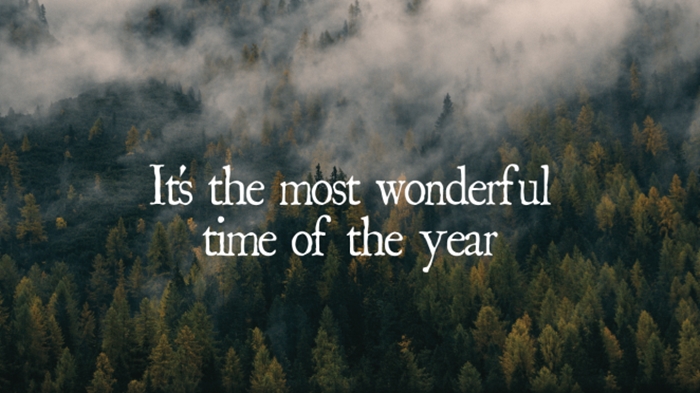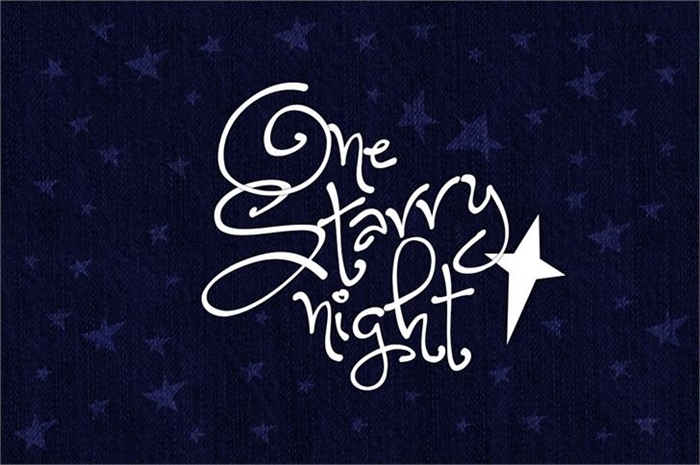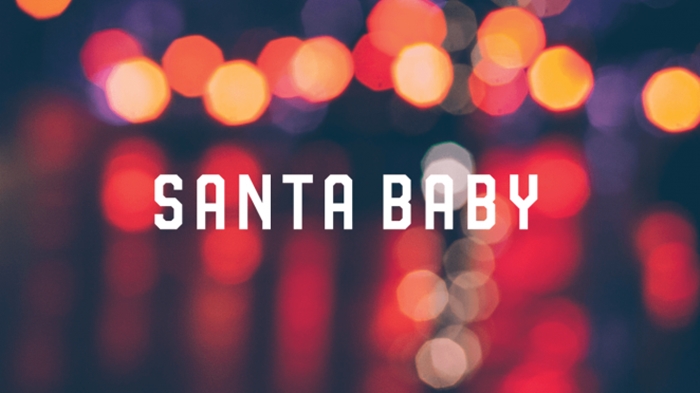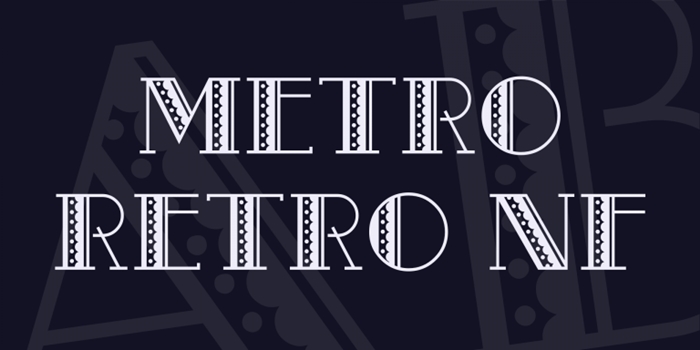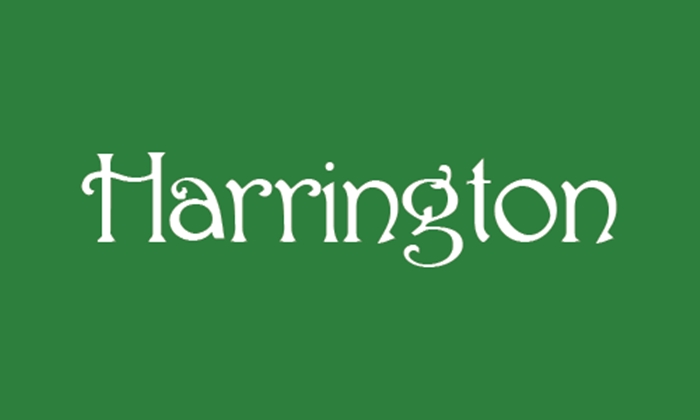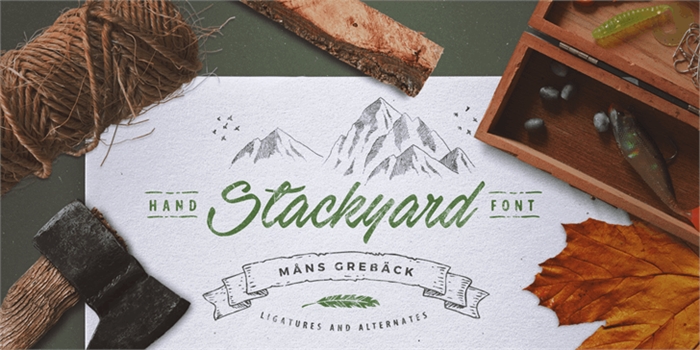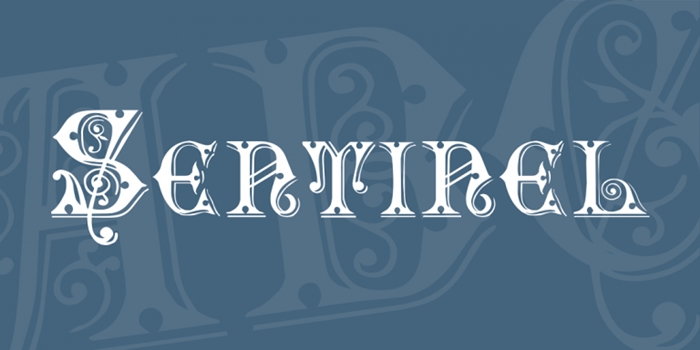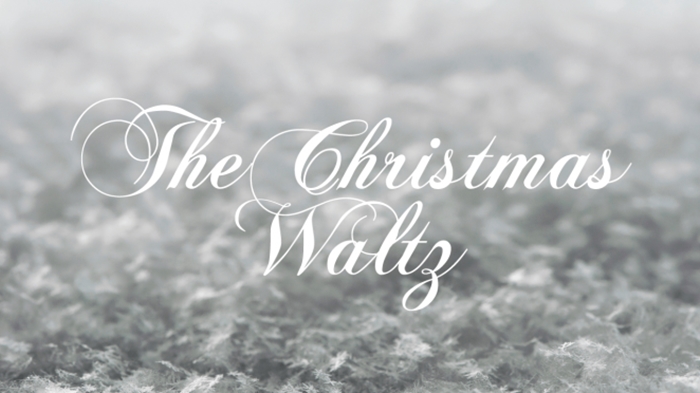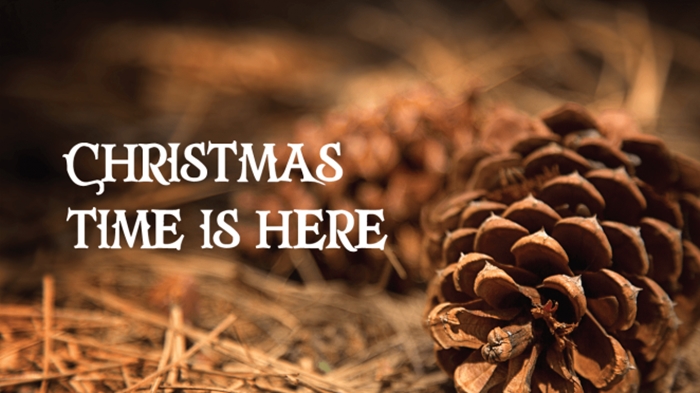
10 ฟ้อนท์สวยๆ ให้ดาวน์โหลดฟรี ต้อนรับเทศกาลวันหยุด
เทศกาลคริสต์มาส มาถึงแล้ว ไม่ทราบว่าใครยังทำงานกันอยู่บ้างค่ะ? ขอให้ยิ้มรับการทำงานอย่างมีความสุขนะคะ และสำหรับคนที่ทำงานด้านดีไซน์ ในบทความนี้เราจะนำลิงก์ในการดาวน์โหลดฟ้อนท์สวยๆ 10 ฟ้อนท์ด้วยกัน ใช้สำหรับเทศกาลวันหยุดนี้มามอบให้กับทุกท่านเพื่อไปใช้งาน
1.One Starry Night.
ฟ้อนท์ให้อารมณ์สนุกๆ แต่มีความสตรองและให้ความรู้สึกถึงพลังเต็มเปี่ยม และยังให้ความรู้สึกอบอุ่นในใจด้วย ดาวน์โหลดฟ้อนท์ที่นี่ Fontspace
2.Metro Retro NF
รูปร่างที่เหมือนเปลือกหอย และไลนเนอร์ที่ประกอบด้วยลายจุดและเส้นบาง ให้ความรู้สึกแนวเรโทรเล็กๆ แต่ยังมีอารมณ์ของช่วงฮอลิเดย์อยู่ด้วย ดาวน์โหลดฟ้อนท์ที่นี่ 1001 Fonts
3.Sentinel
ฟ้อนท์ลายนี้ให้ความรู้สึกที่ยิ่งใหญ่ คลาสสิคก และงดงาม ทั้งนี้ typeface ยังเตือนให้เรานึกถึงหนังสือนิทานที่ไว้อ่านในช่วงเทศกาลวันหยุดอีกด้วย เรียกได้ว่าช่วยให้เราย้อนอดีตนึกถึงความทรงจำสมัยเด็กได้ด้วย ดาวน์โหลดฟ้อนท์ที่นี่ 1001 Fonts
4.Chopin Script
สคริปต์ฟ้อนท์มักจะเป็นตัวเลือกที่ดีเสมอสำหรับการดีไซน์เพื่อเทศกาลวันหยุด และChopin Script ก็เช่นเดียวกัน ตัวอักษรบางๆ กับลายเส้นที่อ่อนช้อย ให้ความรู้สึกเอเลเก้นมากๆ เหมาะจริงๆ กับงานดีไซน์ช่วยเทศกาล ดาวน์โหลดฟ้อนท์ที่นี่ 1001 Fonts
5.Mountains of Christmas
กับลูกเล่นการวางตัวอักษรห่างๆ เล็กน้อยให้อารมณ์ขี้เล่นนิดๆ ได้ดีกับเทศกาลแห่งความสุขนี้จริงๆ นอกจากนี้ ความโค้งมนที่เป็นเอกลักษณ์ของตัวอักษรยังให้คาแร็กเตอร์ที่ดีในช่วงเทศกาล ดาวน์โหลดฟ้อนท์ที่นี่ Font Squirrel
6.St.Nicholas
ฟ้อนท์ลายนี้มอบความรู้สึกแบบช่วงหน้าหนาวได้อย่างดี ตัวอักษรดูมีความแข็งแรง แต่ก็ยังอ่อนนุ่มเหมือนกับหิมะ ดาวน์โหลดฟ้อนท์ที่นี่ DeFont
7.Harrington
ฟ้อนลายนี้คลาสสิคมากๆ แต่ยังแฝงอารมณ์ของความสนุกเอาไว้ด้วย เป็นฟ้อนท์ที่ค่อนข้างสะอาดตา ด้วยลายเส้นบางและความโค้งมน เหมาะอย่างยิ่งกับการทำเป็นเฮดไลน์ ดาวน์โหลดฟ้อนท์ที่นี่ Fontspace
8.Navidad
แม้จะเป็นฟ้อนท์ที่ดูเรียบง่าย แต่ก็ยังให้ความรู้สึกถึงความเป็นฟ้อนท์ช่วงเทศกาลอยู่ การตกแต่โดยการเพิ่ม serif เข้าไปทำให้สัมผัสความรู้สึกที่ดีมากขึ้น และตัวอักษรหนาก็เป็นช่วยเรื่องตกแต่งได้มาก ดาวน์โหลดฟ้อนท์ที่นี่ Fontspace
9.Hand Stockyard Font
ฟ้อนท์ลายนี้สวยมาก คล้ายกับฟ้อนท์พู่กัน แต่ก็ยังให้ความรู้สึกถึงความแข็งแรง และการตวัดลายเส้นเร็วๆ ทำให้ดูงดงามมาก เหมาะกับการใช้งานดีไซน์วันหยุด ดาวน์โหลดฟ้อนท์ที่นี่ Fontspace
10.Party Lights
แม้จะเป็นฟ้อนท์ที่เรียบง่ายแต่ก็ใช้ได้เหมาะกับในหลายเทศกาล ด้วยความที่มันดูสะอาดและตัวหน้า และบางลายยังมีจุดวงกลมด้วย ก็ยิ่งช่วยดึงสายตาให้น่าสนใจมากขึ้น ดาวน์โหลดฟ้อนท์ที่นี่ Fontspace